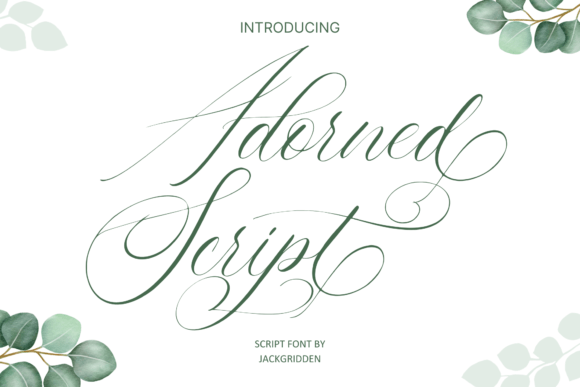
Adorned Script
Adorned Script gibi yüksek kaliteli varlıklar arıyorsanız, bu premium paket yaratıcı projeleriniz için harika bir seçimdir.
İster İsteğe Bağlı Baskı (POD) ürünleri, ister düğün davetiyeleri veya sosyal medya grafikleri oluşturuyor olun, Adorned Script ideal bir uyumdur.